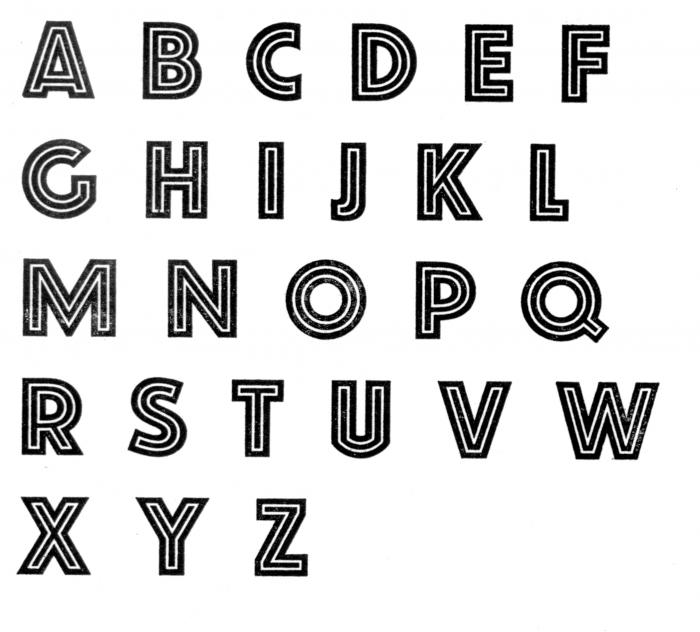
vielleicht könnt ihr mir helfen.
Ich habe in der Handsatzwerkstatt meiner Hochschule diese Schrift gefunden. Angeblich heißt sie Reflexschrift Helios, aber sicher ist man sich auch in der Werkstatt nicht und ich kann nicht einmal in der Deutschen Nationalbibliothek etwas dazu finden.
Kennt jemand diese Schrift und weiß wie sie heißt oder wer sie geschnitten hat?
Die heißt tatsächlich Helios und stammt, wenn ich das noch richtig im Kopf haben sollte, aus der Dresdener Schriftguß-AG, vormals Gebrüder Butter ...
Wäre es möglich, einmal alle vorhandenen Figuren einmal abzuziehen? Also wenn vorhanden auch Gemeine, Ziffern, Sonder- und Satzzeichen?
Ich bin bereits am Digitalisieren der Schrift, da ich mich auch sehr für seltene Schriften, gerade aus dem Handsatz, interessiere.
Es ist eine reine Versalschrift. Es gibt noch Zahlen und ein paar Zeichen. Ich werd mal sehen ob ich in den nächsten Tagen
noch einmal in den Handsatz darf dann stell ich ein Schriftbild gleich online.